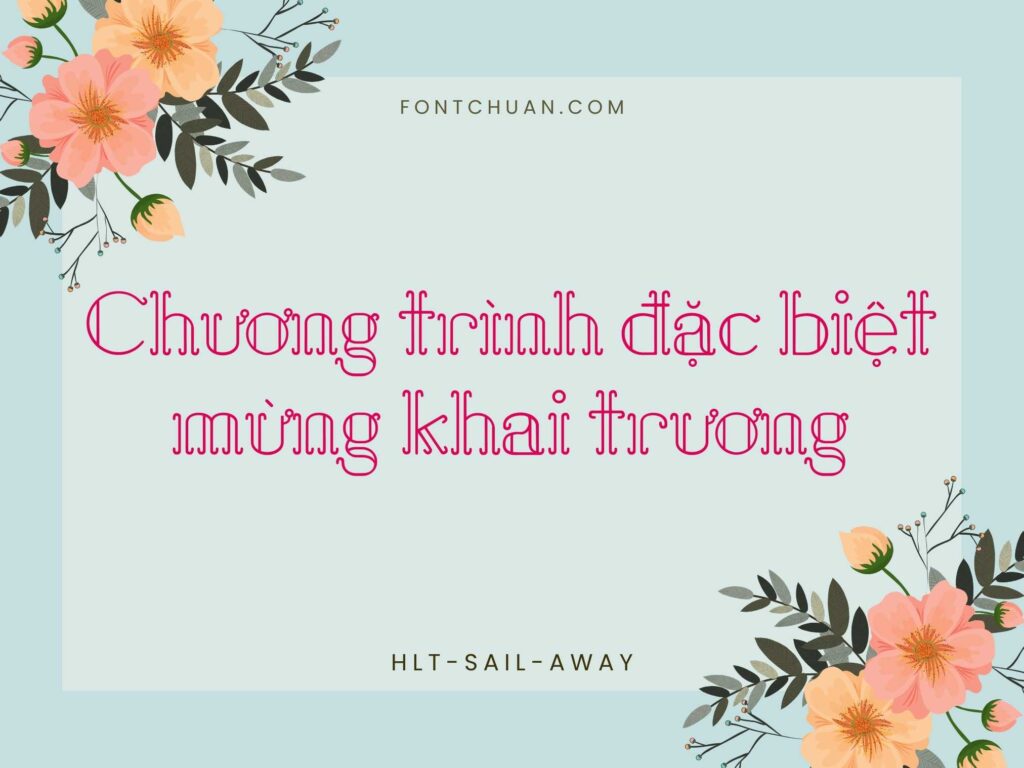
Font HLT Sail Away Việt Hóa
Sail Away là một phông chữ hiển thị trang trí mang phong cách cổ điển, được thiết kế để mang lại vẻ đẹp độc đáo và thu hút. Phông chữ này có những đường nét mềm mại nhưng mạnh mẽ, tạo nên sự phá cách và ấn tượng cho các thiết kế. Với sự Việt hóa của HLT, Sail Away hỗ trợ đầy đủ các ký tự tiếng Việt, giúp người dùng dễ dàng áp dụng trong các thiết kế đa ngôn ngữ. Thành viên của Font Chuẩn đã sưu tầm và chia sẻ phông chữ này nhằm đáp ứng nhu cầu đa dạng của cộng đồng thiết kế.
Về đặc điểm thiết kế, Sail Away có kiểu chữ đậm, các ký tự được thiết kế tinh tế với nét bo tròn và đường nét rõ ràng, mang lại cảm giác cổ điển nhưng vẫn hiện đại. Phông chữ này đặc biệt phù hợp cho các dự án như thiết kế poster, tiêu đề quảng cáo, bìa sách và logo thương hiệu, giúp tạo sự thu hút và chuyên nghiệp. Ngoài ra, Sail Away cũng thích hợp cho các sự kiện như lễ hội, sinh nhật, Valentine và Trung thu, mang lại không khí vui tươi và gần gũi. Trong lĩnh vực ngành nghề, phông chữ này được ứng dụng rộng rãi trong quảng cáo, thiết kế thiệp cưới, giáo dục và công nghệ, góp phần tạo nên phong cách độc đáo và ấn tượng cho các sản phẩm và thương hiệu.